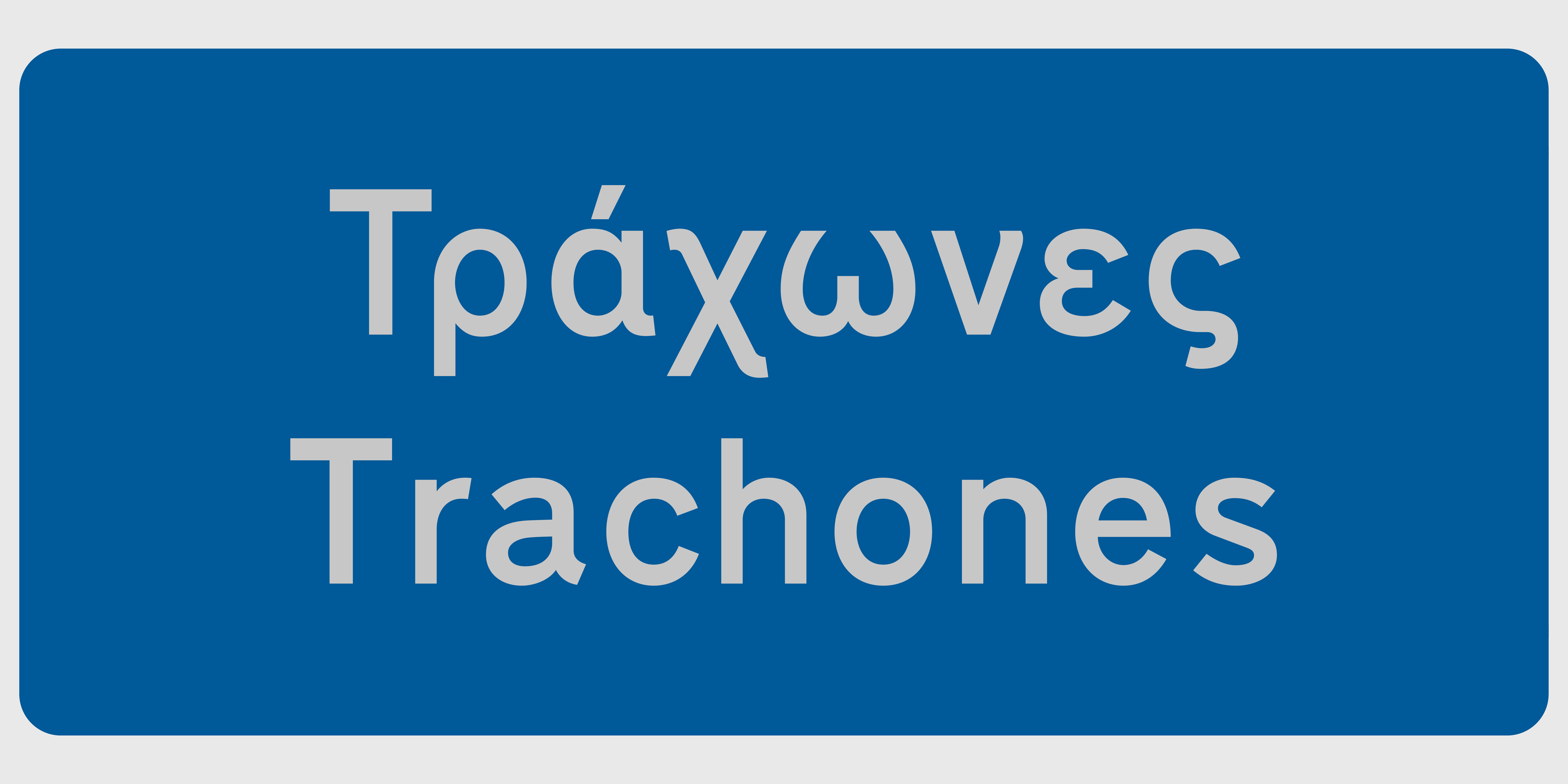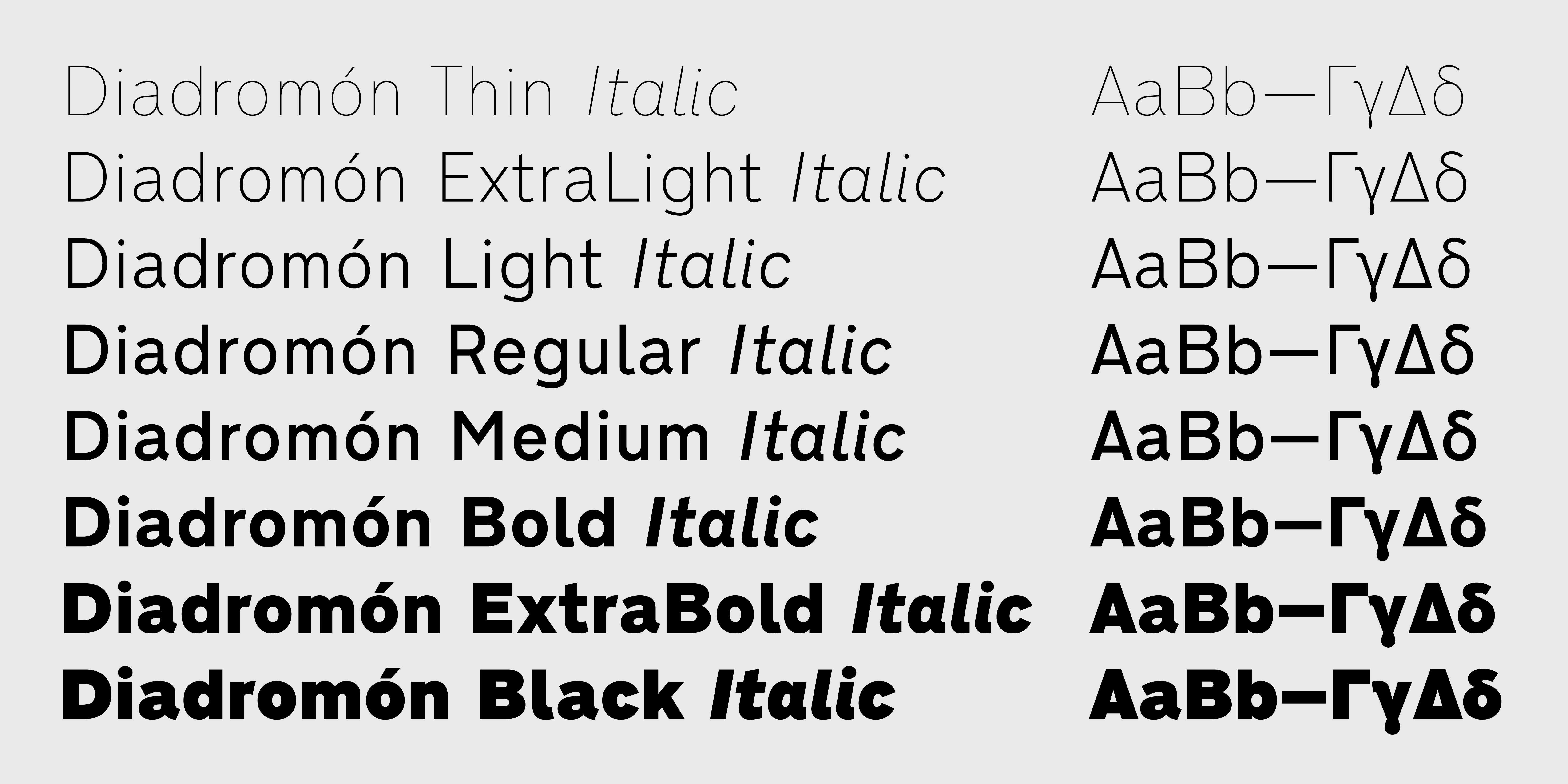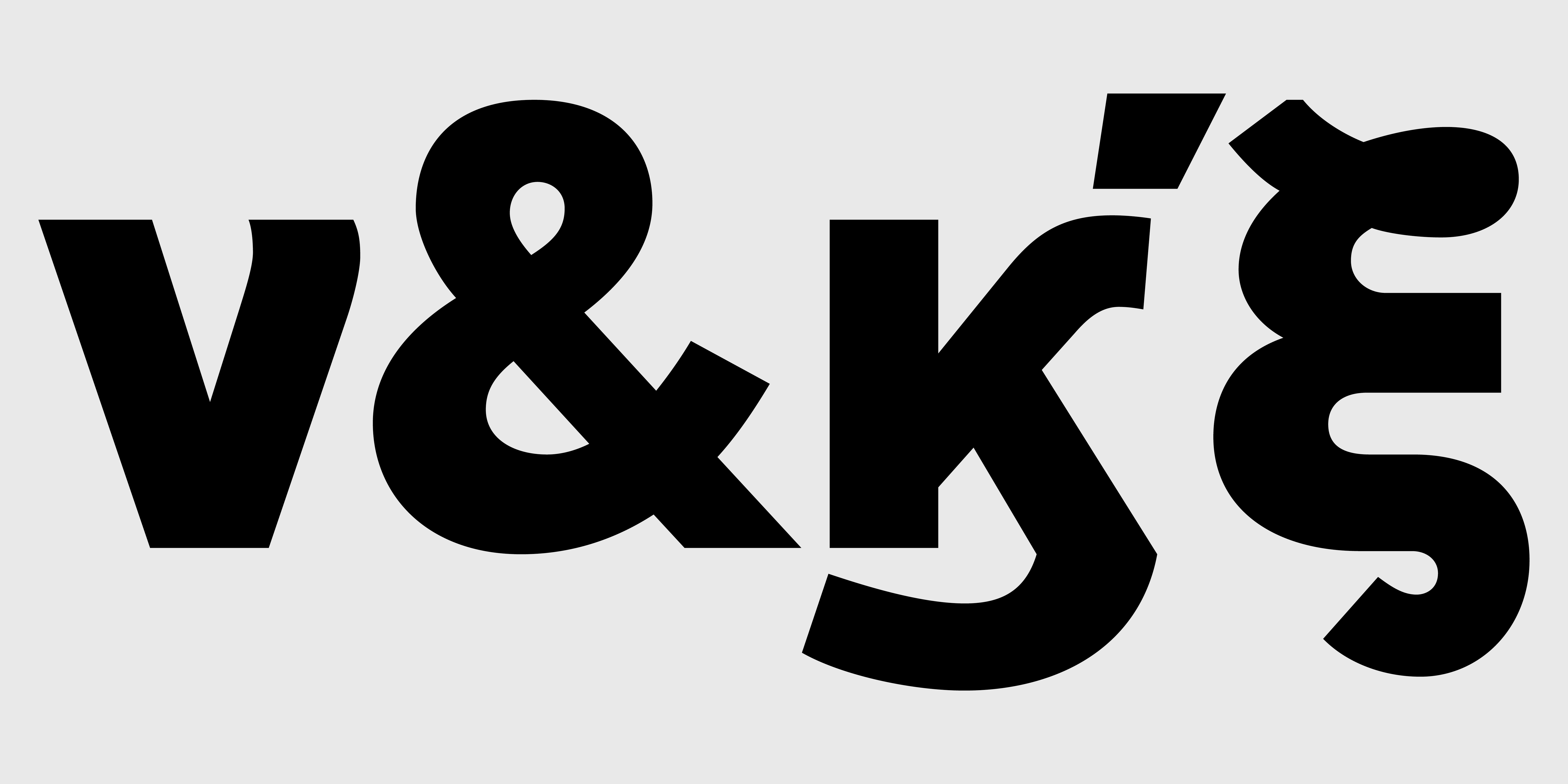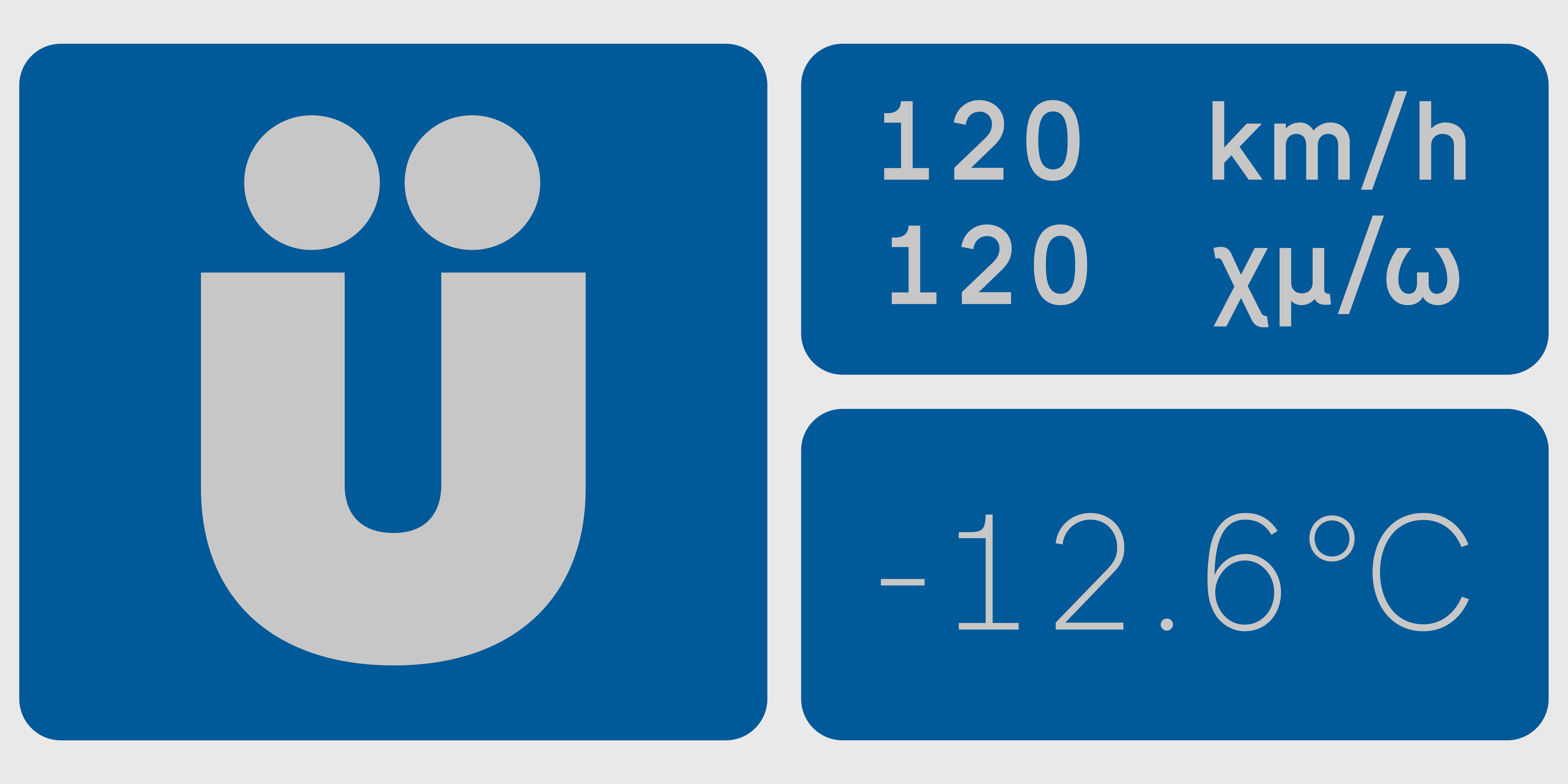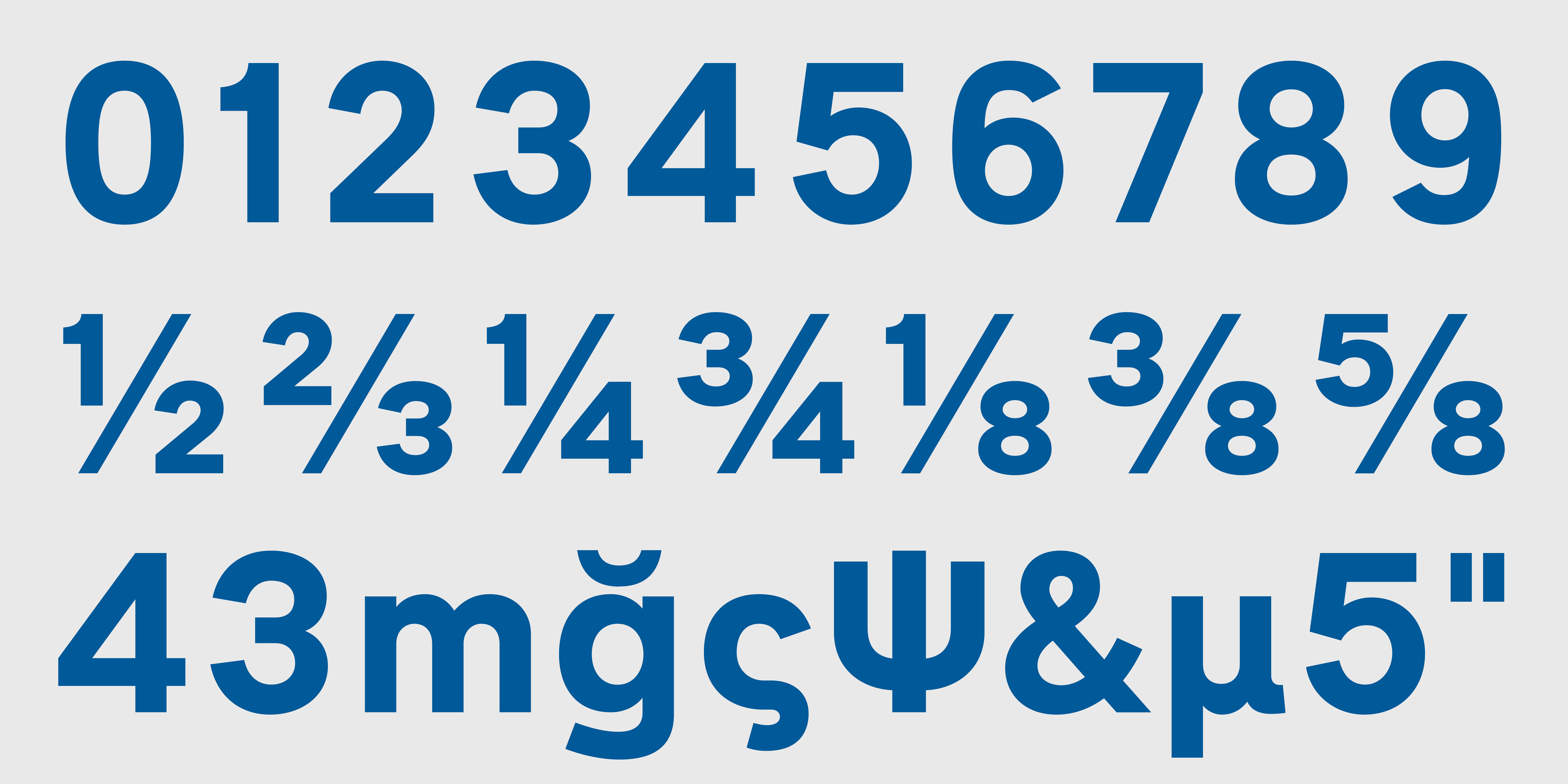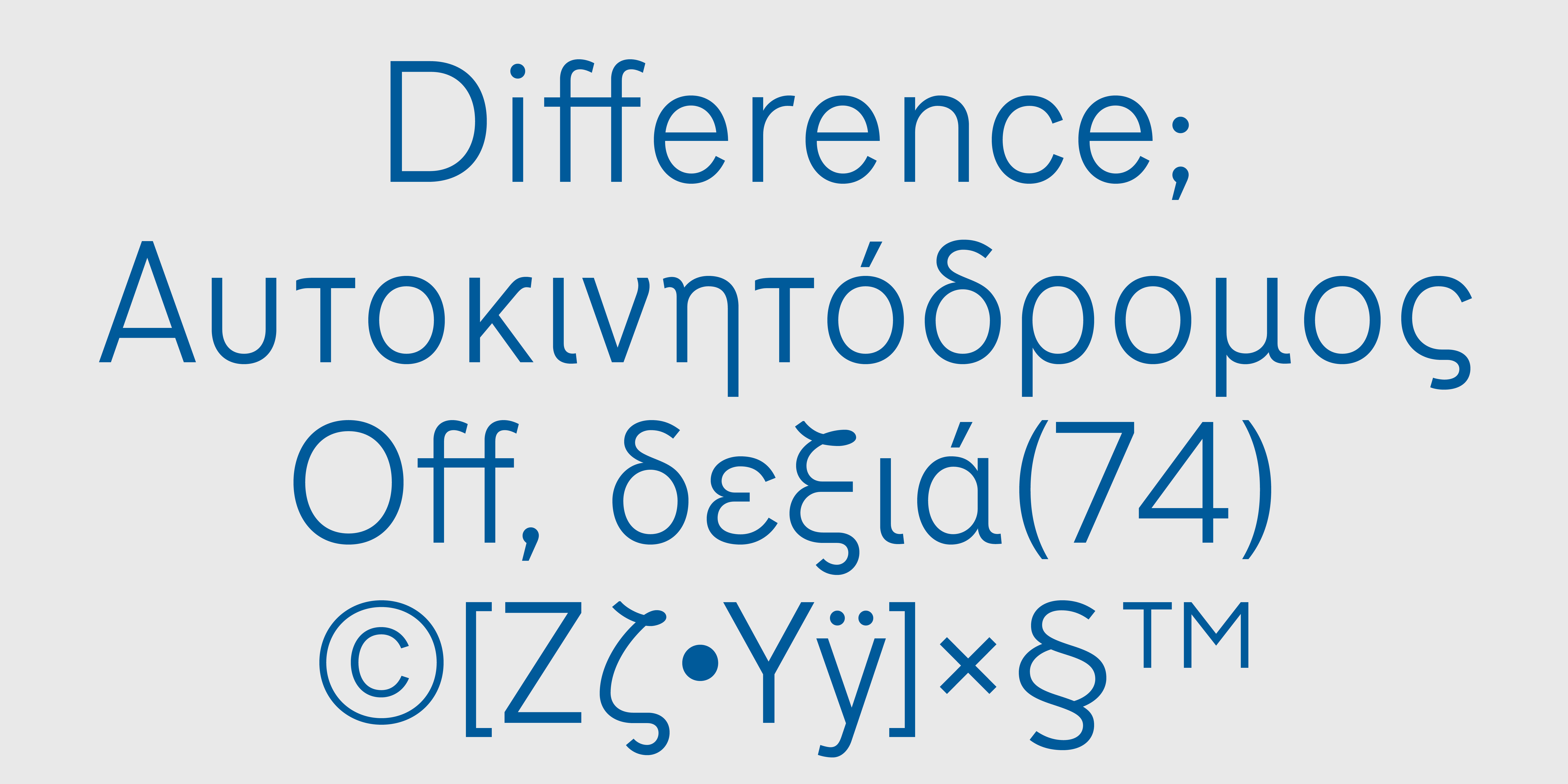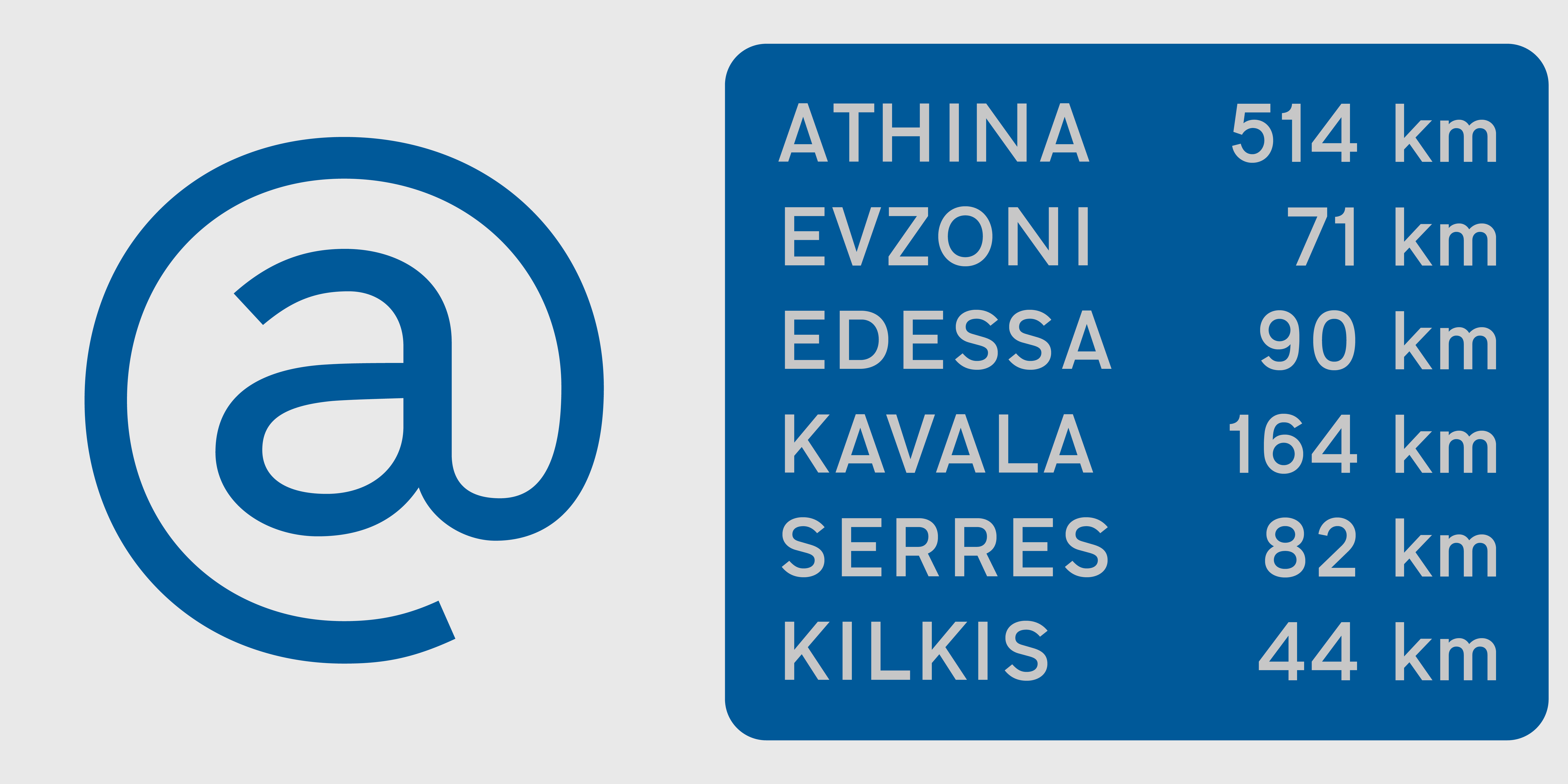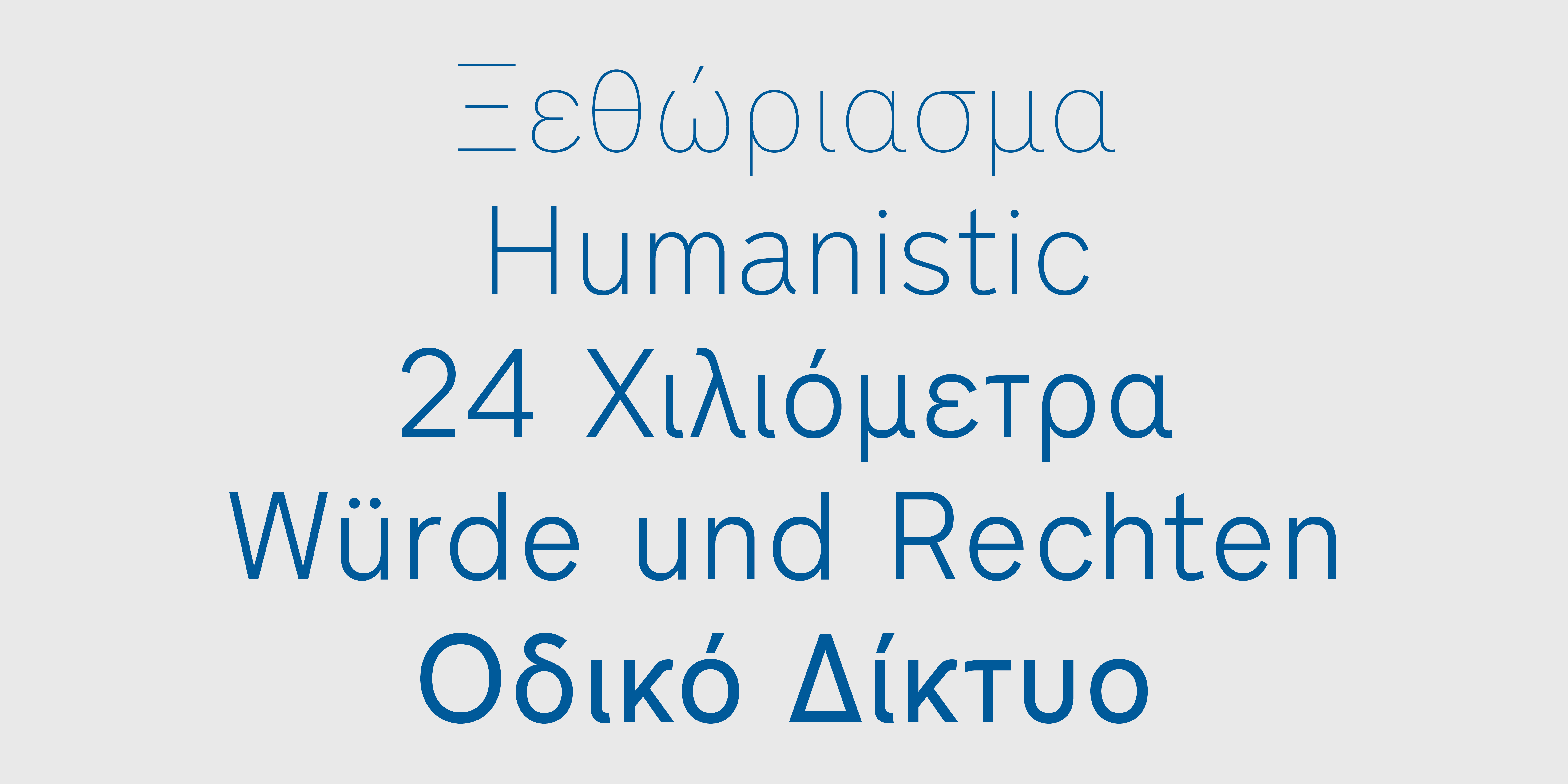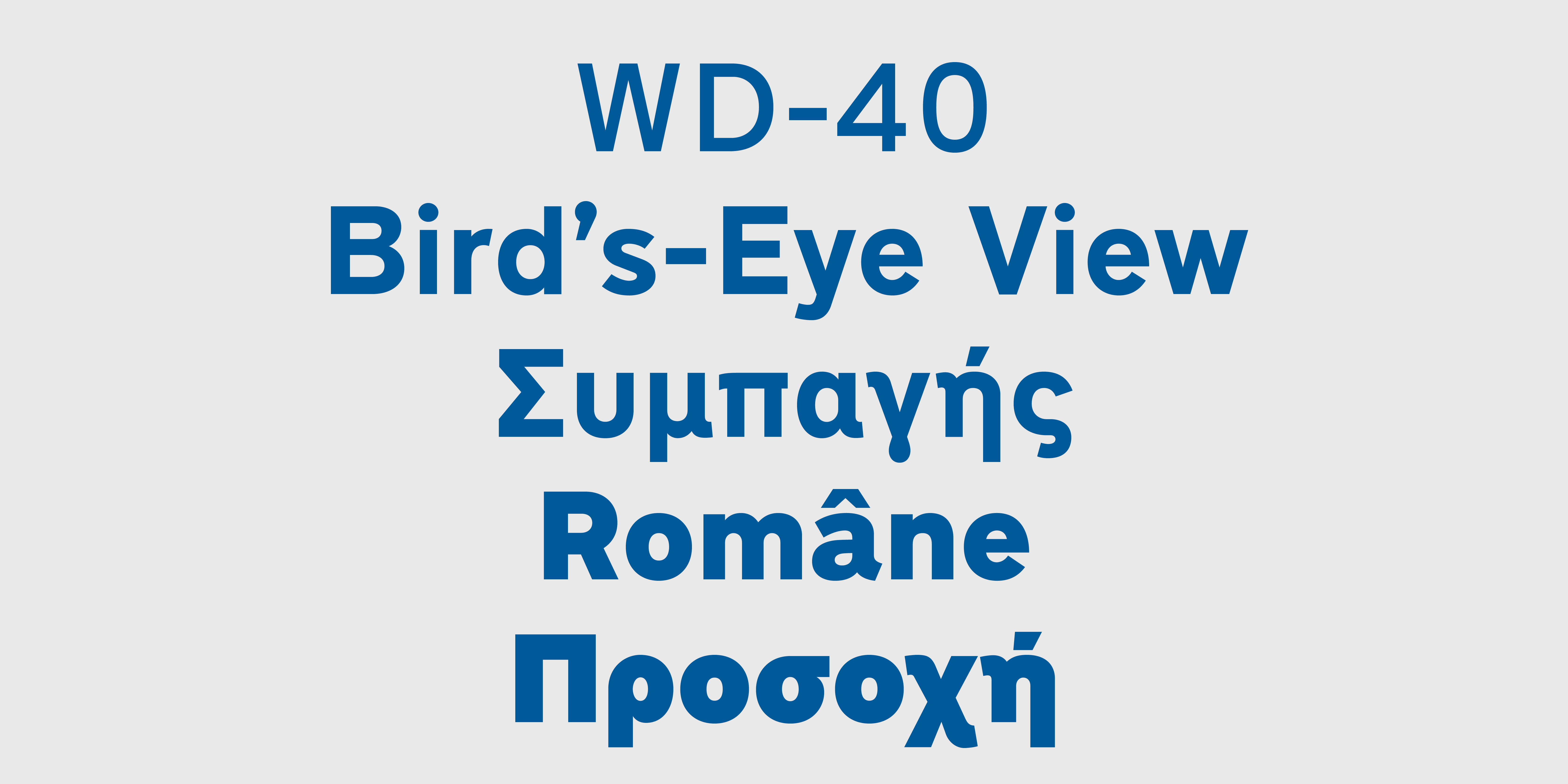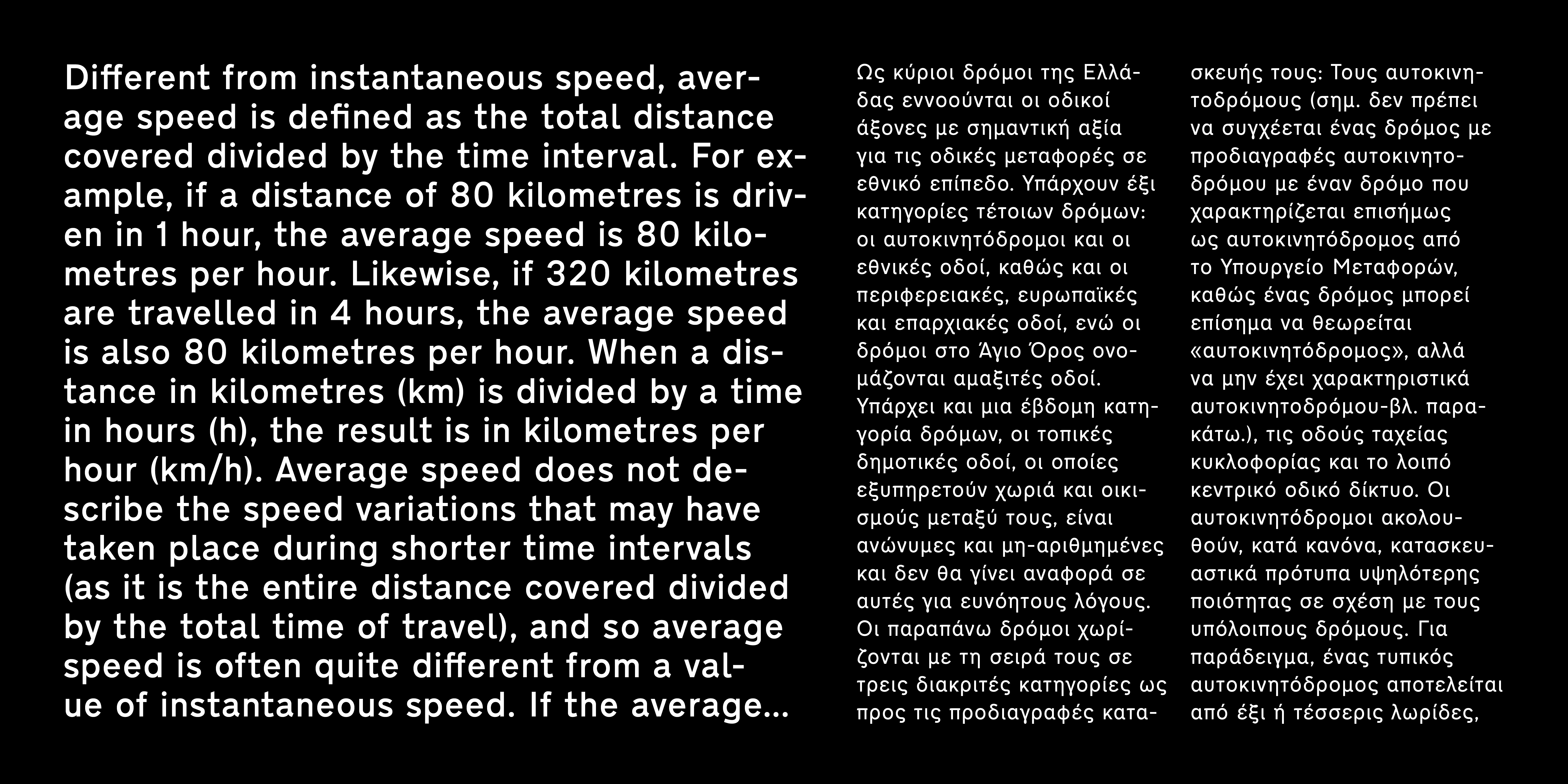
DiaDromon
Η CF DiaDromon σχεδιάστηκε από τον Παναγιώτη Χαρατζόπουλο στο πλαίσιο εργασίας για τον εξορθολογισμό της οδικής σήμανσης. Αποτελεί αναβίωση των γραμμάτων που είναι σε όλους μας γνωστά από τις μπλε πινακίδες των επαρχιακών δρόμων και τοπονύμιων της χώρας. Αρχικά, η γραμματοσειρά της Σήμανσης σχεδιάστηκε και υιοθετήθηκε από το Υπουργείο Δημοσίων Έργων το 1974 έχοντας προκύψει από την προσαρμογή του βρετανικού προτύπου που σχεδιάστηκε από τον Jock Kinneir και τη συνεργάτιδα του Margaret Calvert στη δεκαετία του 60. Η ψηφιακή έκδοση CF Dromon, απαλλαγμένη από λάθη και σχεδιαστικές ασυνέπειες της αρχικής γραμματοσειράς, υποστηρίζει Ελληνικό Μονοτονικό και πλήρες Δυτικό Λατινικό σύνολο χαρακτήρων (συμπ. Ρουμανικών και Τουρκικών), αριθμούς σταθερού πλάτους, κλάσματα κ.λπ. Το 2017 η CF Dromon εμπλουτίστηκε με νέα βάρη.